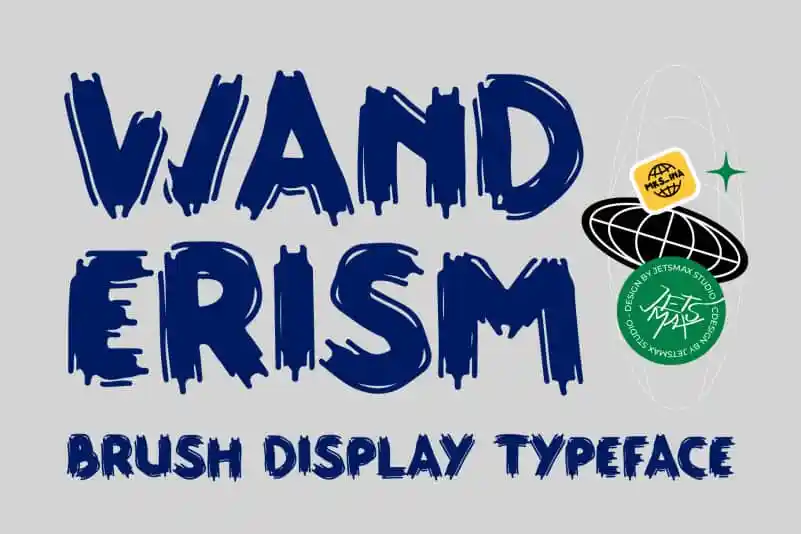
Wanderism Brush Font – Download Grátis
A Wanderism Brush Font é uma seleção ideal para aqueles que buscam uma nova aposta em seu design digital. Esta fonte brush carrega influências de graffiti neo-graffiti, oferecendo um toque moderno e fresco às suas criações digitais. Ela será particularmente apropriada se você estiver procurando por elementos inovadores e autênticos para seus trabalhos que precisam de uma reviravolta ou um toque de originalidade. Seja em projetos gráficos, publicações online ou qualquer outro aplicativo digital que você esteja desenvolvendo, a Wanderism Brush Font certamente fará sua marca. Com seu estilo fresco e vibrante, ela não só adicionará uma nova dimensão à sua composição, mas também garantirá um toque único em seus projetos digitais. Para designers desejosos de um design que se destaca, a Wanderism é definitivamente o caminho para alcançar isso.
Designer: jetsmax